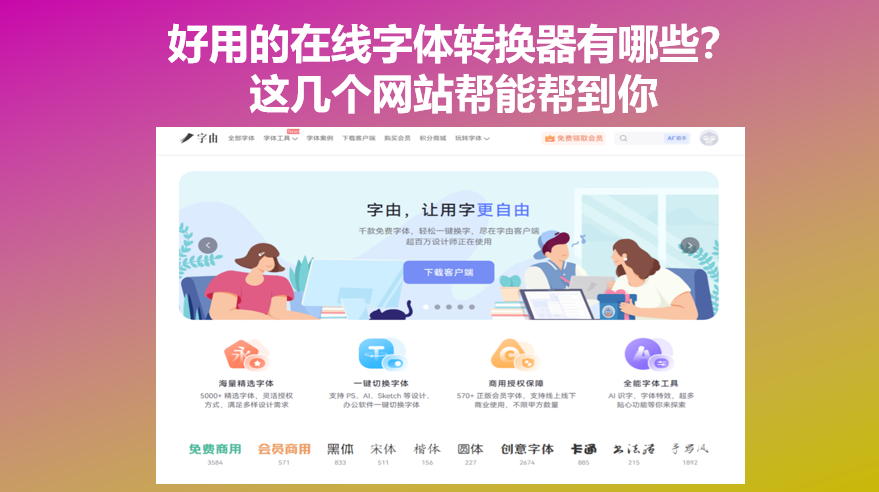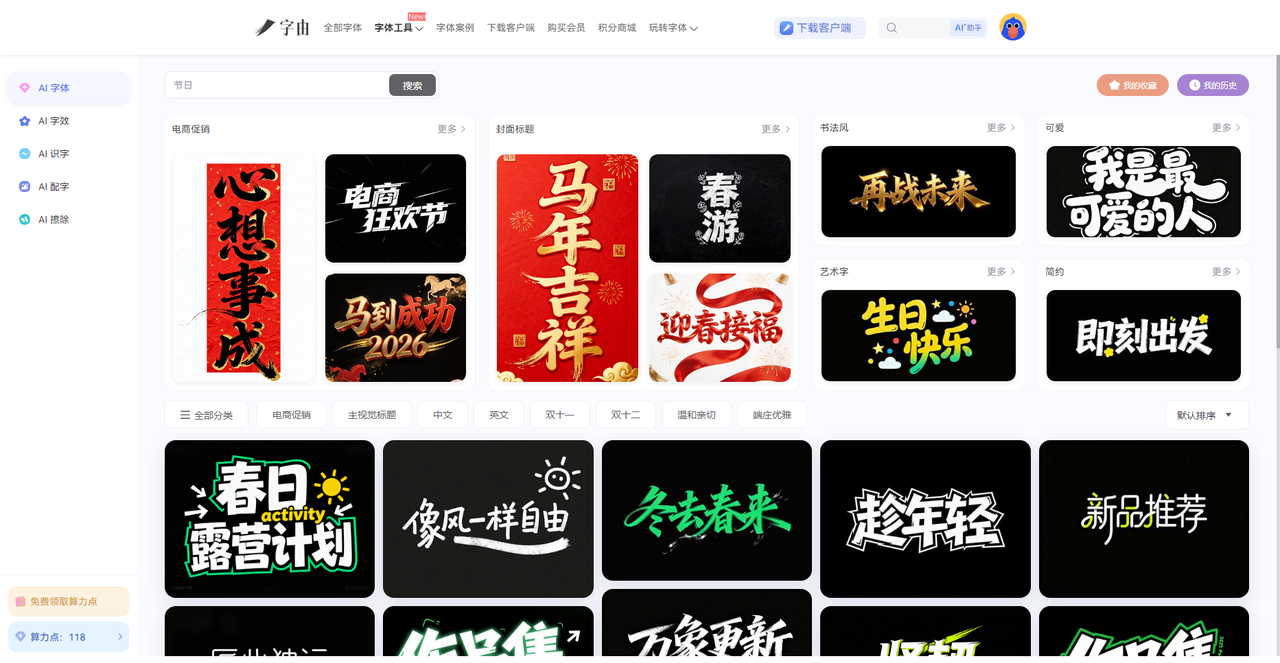
好用的在线字体转换器有哪些?这几个网站帮能帮到你
打开浏览器,随手搜索“字体转换器”,大部分结果都是花体字生成器。它们很方便,输入文字,复制粘贴,就能在社交媒体上用上不一样的字体。但很多时候,设计师或内容创作者的场景更复杂:可能是想把下载的字体文件转换成网页可用的格式,也可能是想快速给海报标题加上金属或霓虹特效,又或者是想批量生成某部电影风格的标题字。今天我就为各位设计师整理了5 个各有侧重的在线字体转换器。它们能帮你处理的,不只是简单的字体转换。
很多人使用字由是从字体库开始的。你不需要下载客户端,直接在字由官网的字体详情页或搜索结果中,就能输入文字实时查看不同字体的应用效果,快速筛选出符合项目调性的样式。这种方式尤其适合在做品牌VI或海报时,需要从几十款候选字体中做抉择的场景。
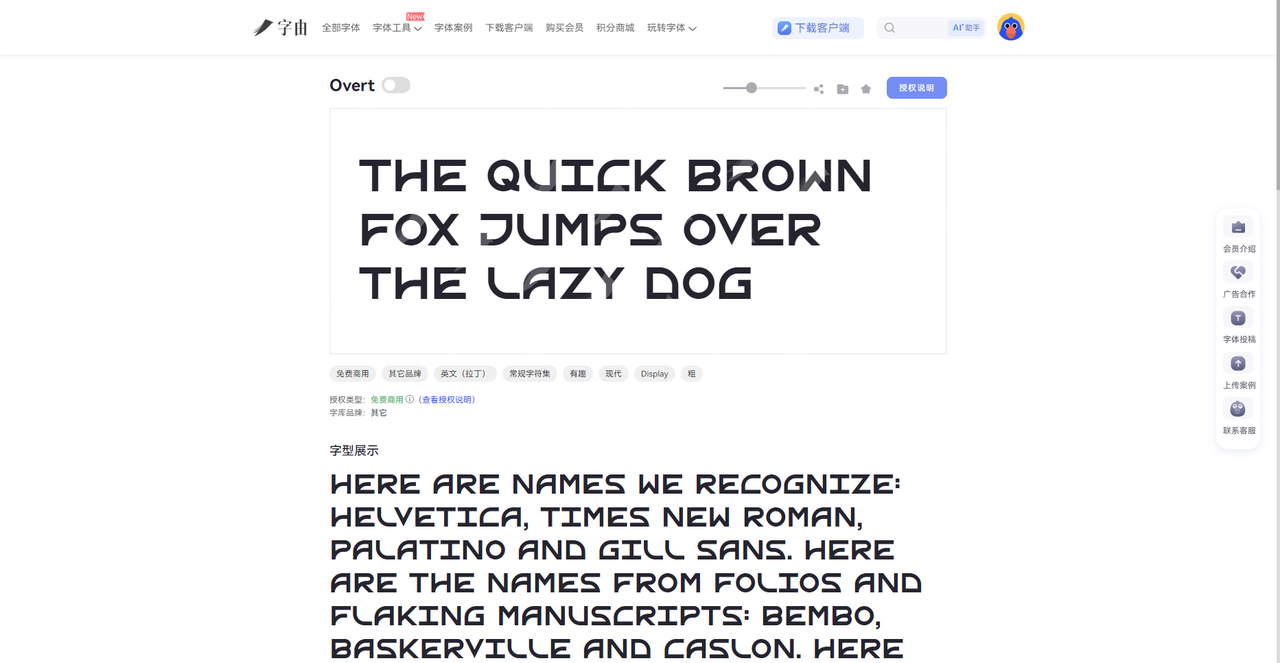
决定用哪款字体后,在线字体转换器的第二个方法就来了,字由最大的技术亮点是它的“字体激活”机制——你不需要把字体文件安装到系统目录,只需在客户端点击“激活”,字体即可在所有支持OpenType的设计软件(如PS、AI、Sketch)中生效。这相当于把“下载-安装-重启软件”这一长串步骤,压缩成了一键操作,使用谁知道。
除此之外,字由的AI字体功能为“转换”提供了第三种可能。它内置了多种字体特效模板,覆盖电商、游戏、新媒体、品牌海报等不同场景。输入你的文案,选择一个金属质感或霓虹灯风格的模板,不到30秒就能生成一张可直接下载的PNG艺术字图片。
2、Cool Fancy Text Generator
第二个网站是一个功能非常全的在线花体字生成器,它提供了 387 种不同的字体样式。输入文字后,页面会列出所有可用的转换结果,包括花体、哥特体、气泡体、粗体、斜体、小型大写等。
这个工具最大的特点是“全”。387 种样式意味着你几乎能找到所有常见的 Unicode 花体字类型,不用在不同网站之间来回切换。生成结果支持一键复制,粘贴到 Instagram、Twitter、Discord、微信等平台都能正常显示。
界面设计比较简洁,输入框在顶部,下面直接列出所有样式,没有多余的功能干扰。如果你是一个喜欢尝试不同字体风格的人,或者需要给不同项目配不同风格的标题,这个 387 种样式的生成器可以当做一个“字体库”来用——输入文字,扫一遍结果,看到喜欢的就复制。
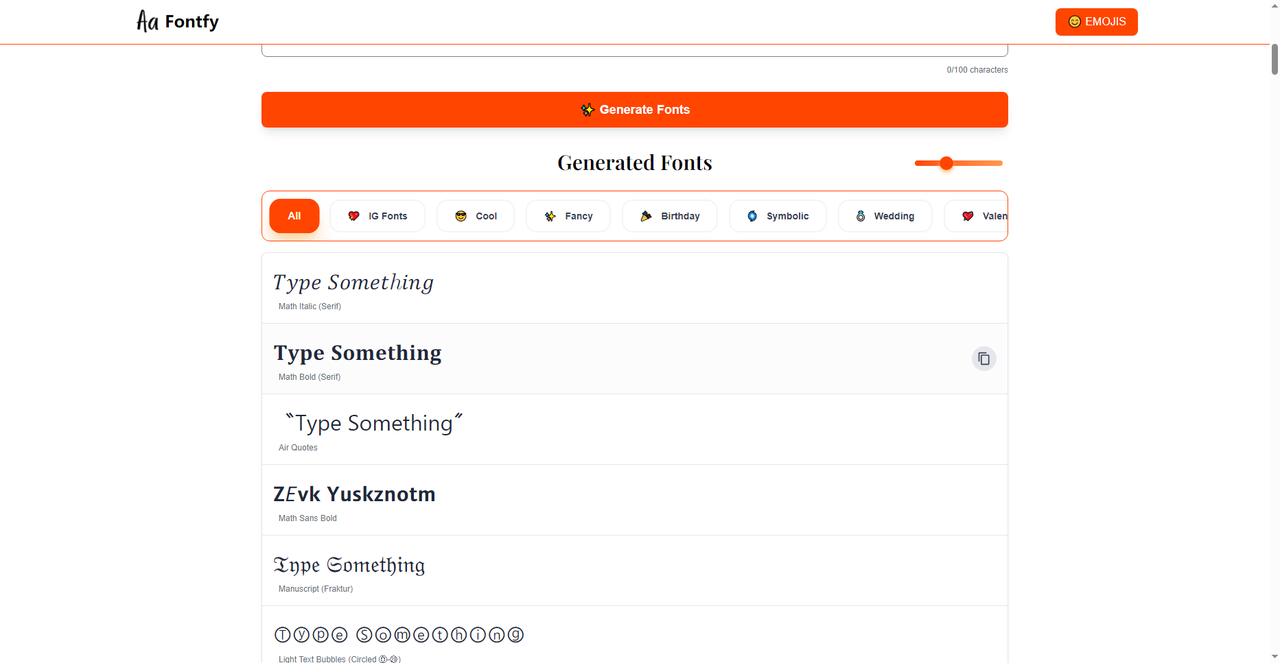
3、FONTY
第三个工具是 Fonty。它和其他在线生成器不太一样,主打的是移动端体验——提供 iOS App 下载,Android 版本也即将上线。Fonty 提供了 80 多种独特的字体样式,覆盖粗体、花体、草书、符号体等类别。它的核心使用场景是:在手机上直接打出花体字,然后粘贴到 Instagram、TikTok、WhatsApp 等 App 里。不需要在浏览器和社交 App 之间来回切换,Fonty 自己就是一个“支持花体字的键盘”。除了字体转换,Fonty 还内置了智能剪贴板和 AI 写作助手,可以帮助用户润色文案、生成创意内容。如果你经常在手机上发社交媒体内容,又想让文字更有风格,Fonty 的 App 模式比网页工具更方便——打字的时候直接选字体,不用复制粘贴的步骤。
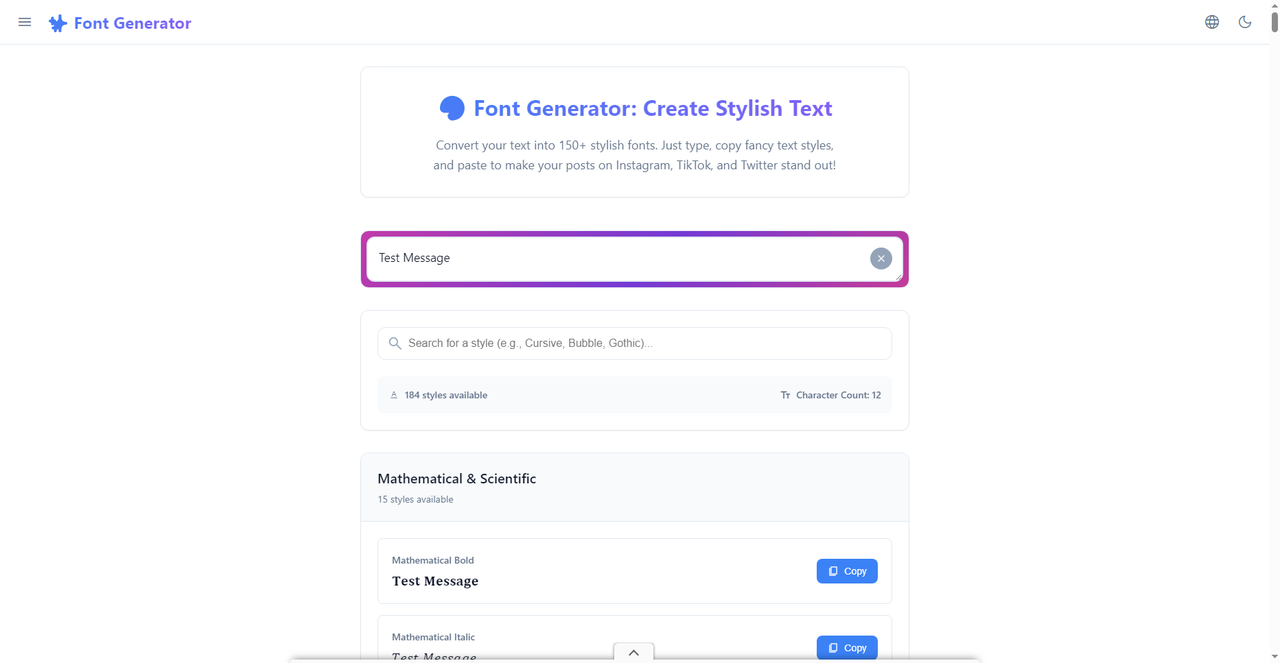
4、Font Generator
第四个工具是一个功能偏向“学术”和“专业”的在线字体生成器。它提供了 150 多种字体样式,最大的特色是包含了大量数学符号、科学排版相关的字体——比如 Mathematical Bold(数学粗体)、Mathematical Italic(数学斜体)、Mathematical Bold Italic、Sans-Serif(无衬线体)、Bold Script(粗体草书)等。这类字体对于需要在社交媒体上分享数学公式、物理笔记、编程代码的用户来说非常实用。普通的花体字生成器通常不包含这些特殊符号,而这款工具把学术场景也覆盖到了。它的操作方式和同类工具一样:输入文字,选择样式,点击复制。界面左侧有分类导航,可以按 Mathematical & Scientific、Script/Cursive、Sans-Serif 等类别快速筛选。
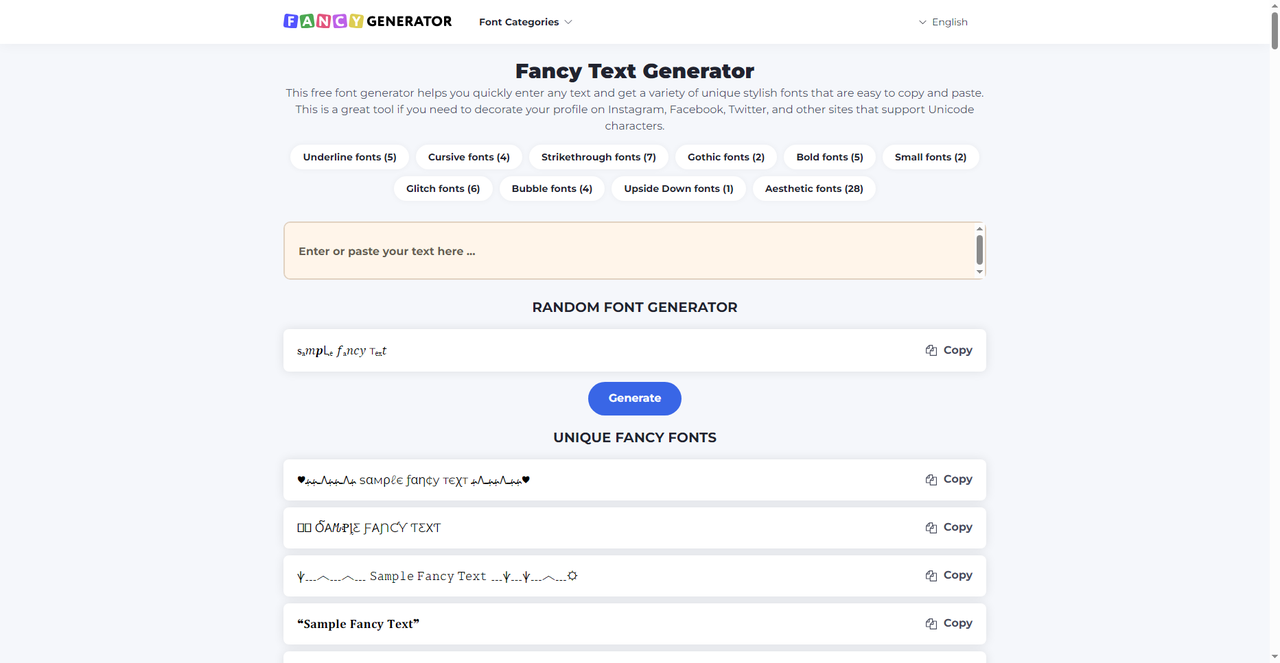
5、Fancy Text Generator
第五个工具是 Fancy Text Generator,一个分类非常细致的在线字体转换器。它的分类栏包括:Underline fonts(下划线字体,5 种)、Cursive fonts(草书字体,4 种)、Strikethrough fonts(删除线字体,7 种)、Gothic fonts(哥特字体,2 种)、Bold fonts(粗体,5 种)、Small fonts(小型字体,2 种)、Glitch fonts(故障艺术字体,6 种)、Bubble fonts(气泡字体,4 种)、Upside Down fonts(倒置字体,1 种)、Aesthetic fonts(美学字体,28 种)。还提供了一个“随机字体生成器”按钮,点一下随机切换样式,适合找灵感。
分类清晰是它最大的优点。如果你明确知道想要什么风格——比如“我想要气泡体”——直接点 Bubble fonts 分类,下面只有 4 种,不用在几百个结果里翻。Aesthetic fonts 有 28 种,涵盖了当下流行的 ins 风、奶油风等样式,适合做社交媒体配图。这个工具还支持“随机生成”功能,如果你不确定用什么风格,点一下 Generate,它会随机展示一种样式,给你一些意外惊喜。
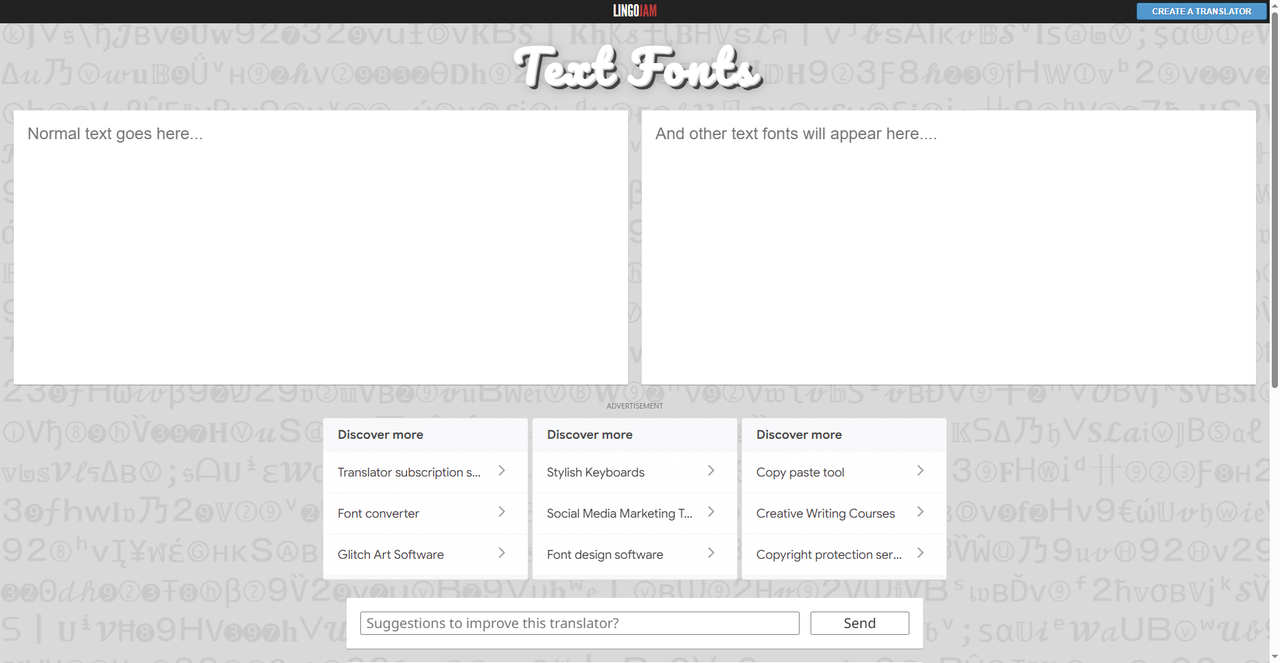
这几个说下来以后,字由的在线预览功能最适合设计师在字体选型阶段快速对比效果,确认好了再激活使用;这也解决了我们一开始说到的一些问题,其他的工具当然也很好用,如果看综合功能的话确实字由要更胜一筹。不论如何,选哪个取决于你当下的需求,设计师们要勤利用网络上的资源,才会提高设计效率和质量。